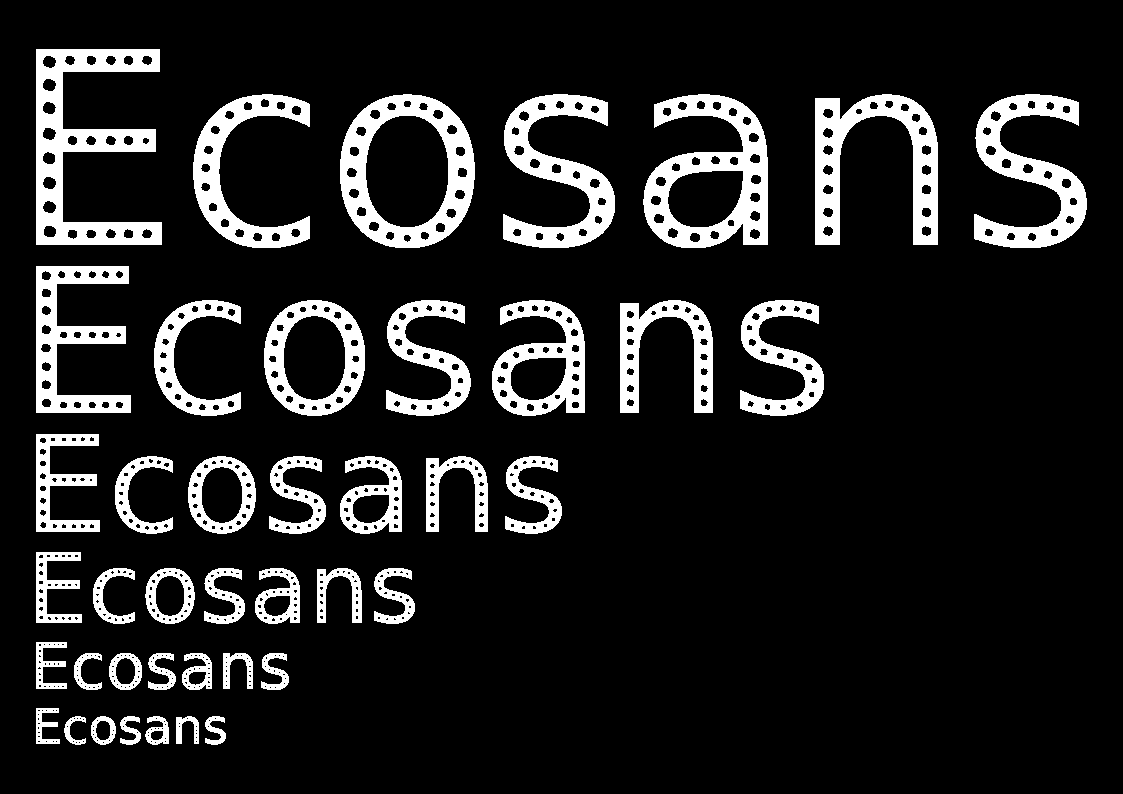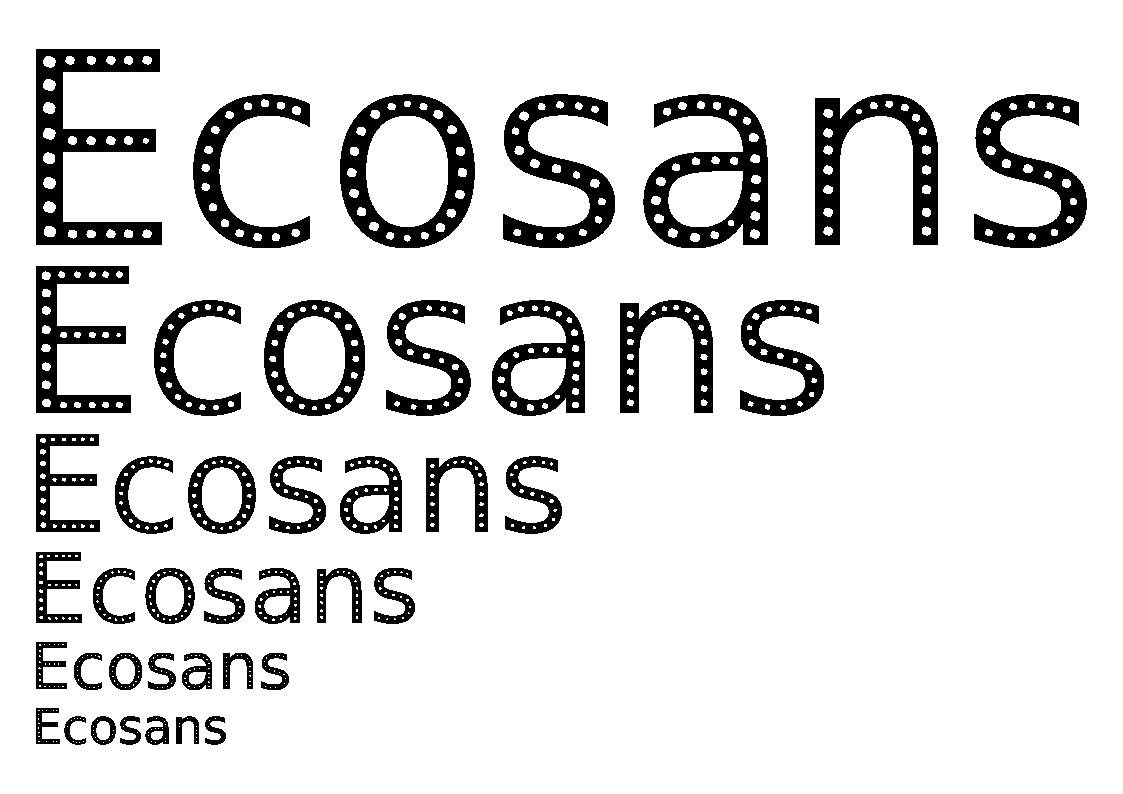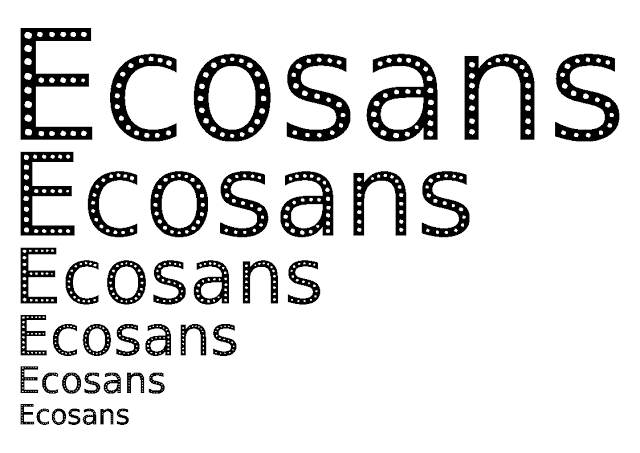
Una tipografía “ecológica”
Las impresiones que hacemos a diario no sólo usan papel, sino que también utilizan tinta. ¡Mucha tinta! Esto es en parte innecesario según SPRANQ Comunicaciones Creativas (Utrecht, Holanda). Por eso SPRANQ desarrolló una nueva tipografía: Ecofont.
“Después del queso holandés con agujeros, ahora hay una tipografía holandesa también con agujeros”.
Las ideas más atractivas son simples: ¿Cuánta tinta se puede eliminar de una letra sin que esta pierda su legibilidad? Tras extensas pruebas con todo tipo de formas. Los mejores resultados se obtuvieron usando círculos pequeños. Después de largas horas (y café) se obtuvo una tipografía que gasta hasta 20% menos de tinta por impresión. De descarga gratuita y de uso gratuito.